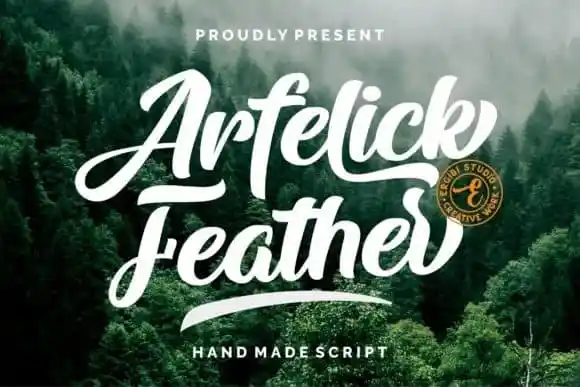
Arfelick Feather Script Font – Fonte Grátis
Arfelick Feather Script Font
A Arfelick Feather Script Font é uma elegante fonte script que se destaca por seu design exclusivamente pensado para logotipos. Ela foi projetada e compartilhada pelo designer Riyadh Rahman. Esta tipografia é um tipo de escrita a mão finamente elaborada, criada para transformar seus trabalhos em verdadeiros ícones. Mantendo suas influências clássicas do caligrafismo, ela mantém um toque contemporâneo e moderno. Estou disponível para aqueles que querem dar um toque de originalidade aos seus projetos gráficos, elevando-os a um nível superior. Descubra porque o mundo dos designers está se encantando com esta Arfelick Feather Script Font.